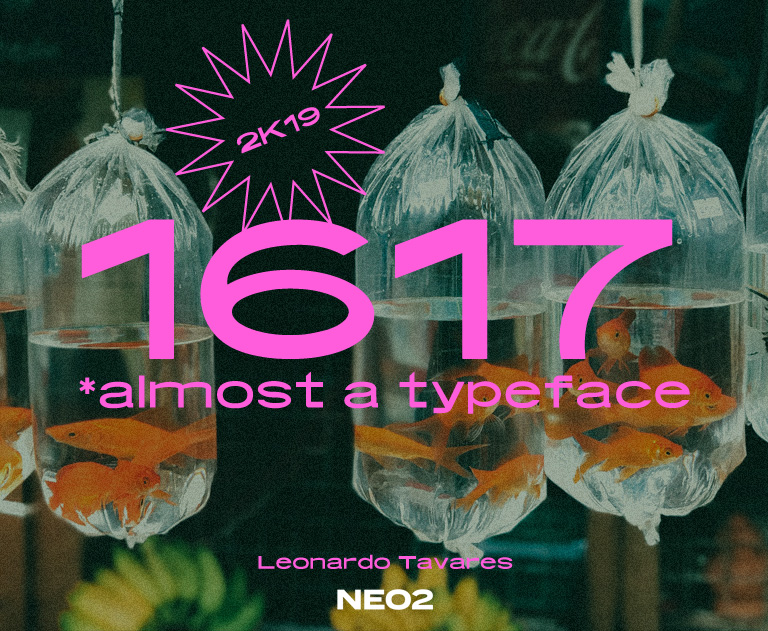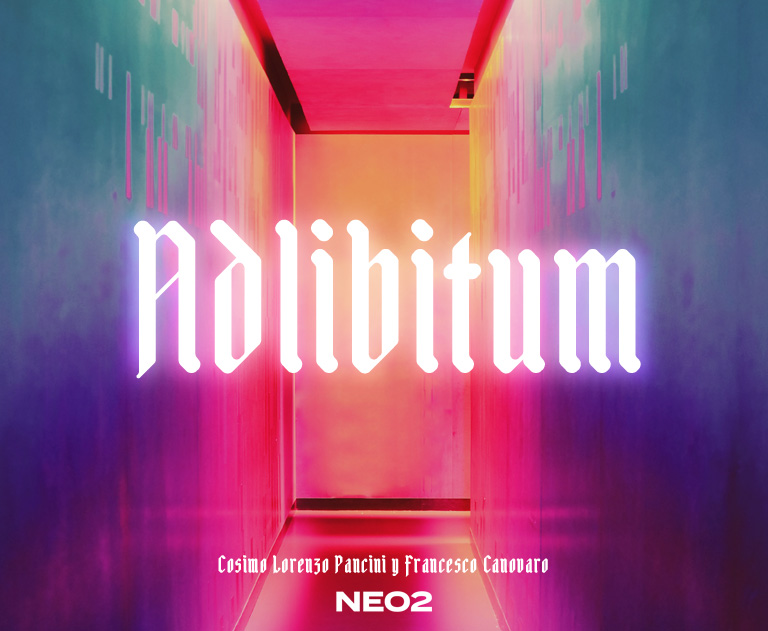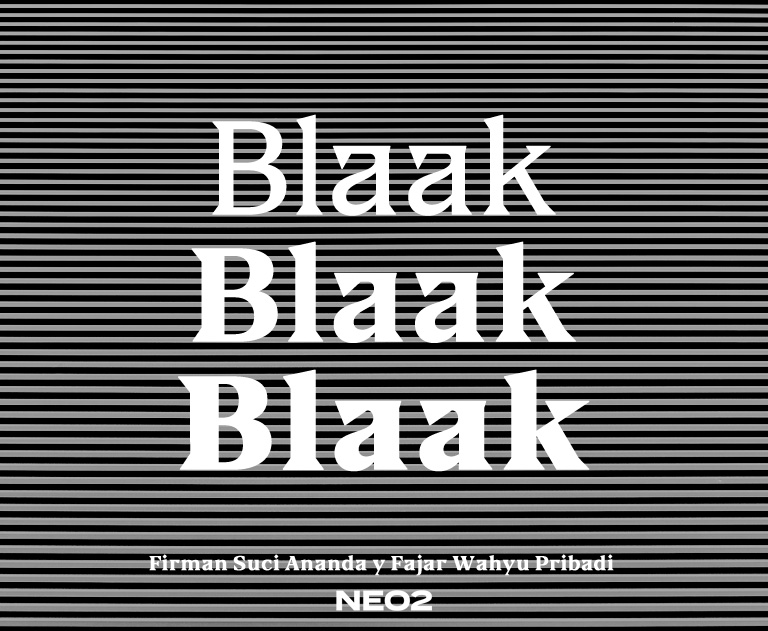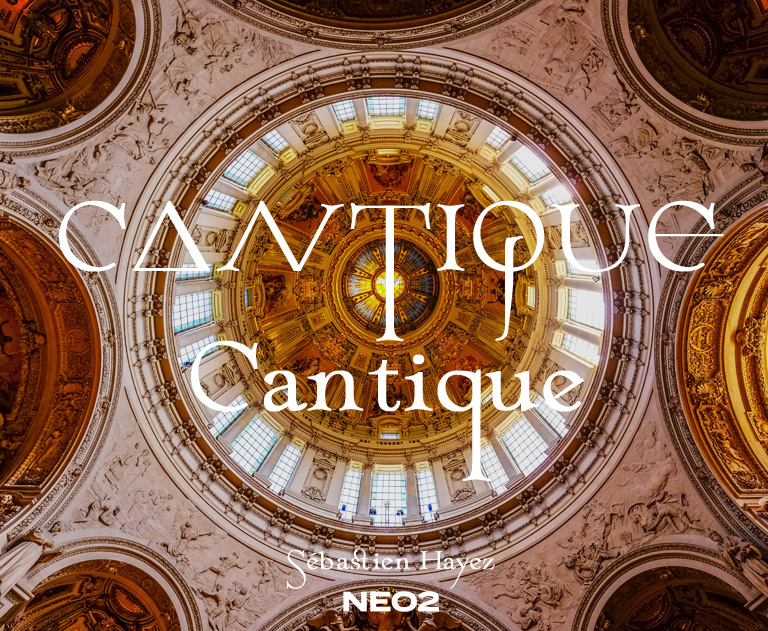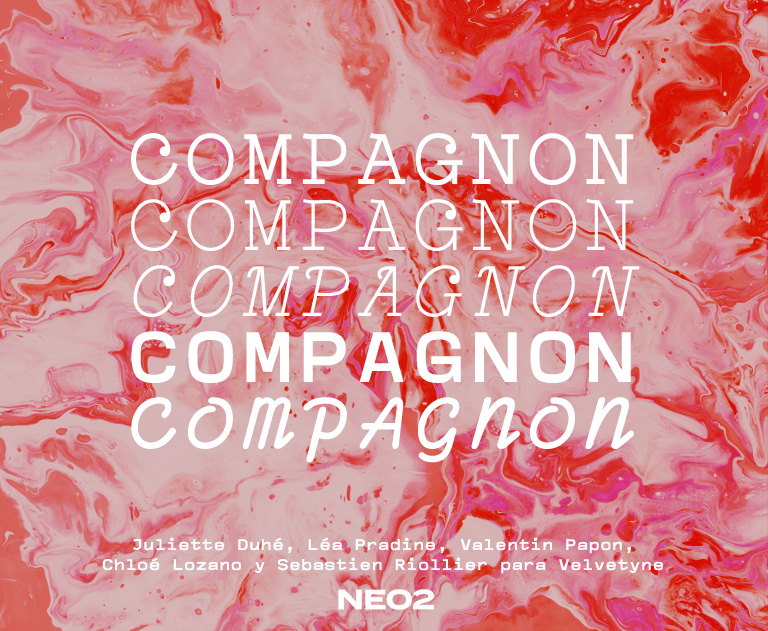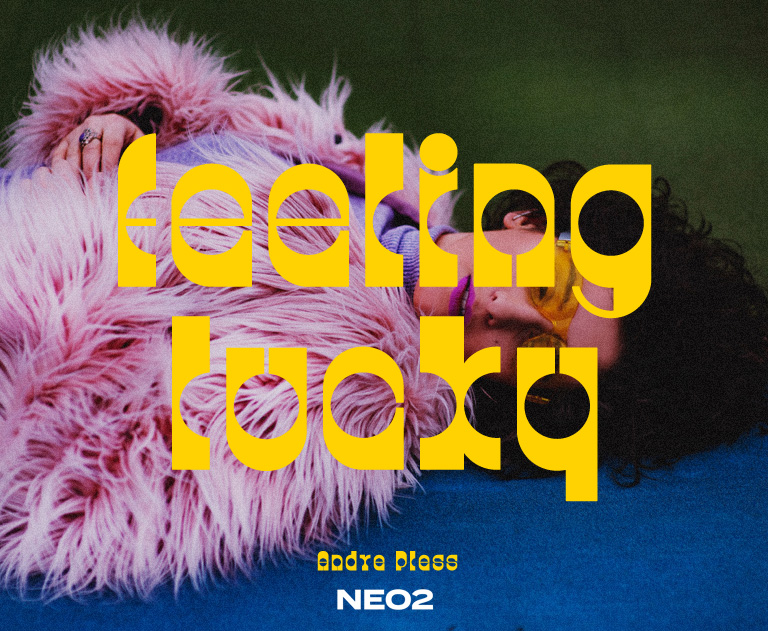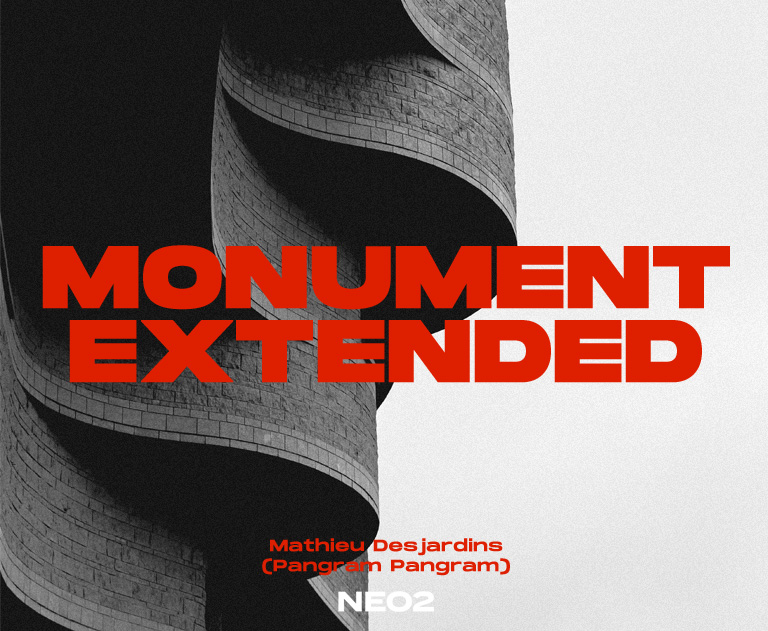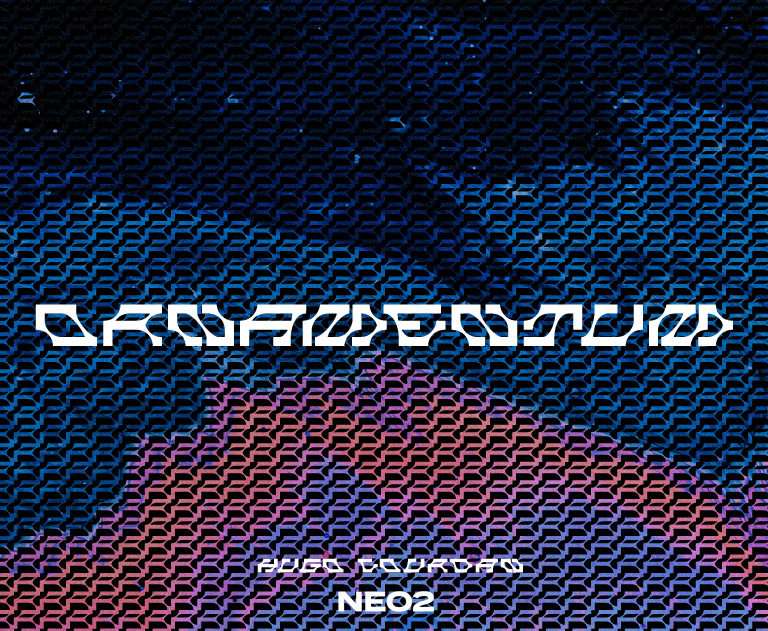
8 tipografías gratuitas que ya deberías tener
Te hacemos una selección de 8 tipografías gratuitas que deberías tener ya en tu ordenador. Las tipografías son una de las herramientas más importantes para los diseñadores, y sabemos que a veces es abrumador la cantidad de ellas que hay.
Pero en Neo2 nos gusta pensar que en la variedad está el gusto. Por eso, hemos creado esta selección de tipografías de distintos estilos que ya deberías tener en tu repertorio.Todas pertenecen a nuestra colección de tipografías gratuitas disponibles para que cualquier fan de Neo2 pueda descargarlas. En esta recopilación hemos escogido algunas de las mejores de los últimos meses. Y nos preguntamos, ¿por qué elegir? Son gratuitas, ¡puedes tenerlas todas!
En esta lista te explicamos qué cualidades hacen a cada tipografía tan especial, y te las mostramos con estos sencillos especímenes que hemos diseñado.
1) Monument Extended, por Mathieu Desjardins (Pangram Pangram)
Esta tipografía gratuita tiene una estética brutalista y muy contemporánea. Se caracteriza por el grosor tan fuerte de sus líneas y por la proporción de sus letras, que son anchas y de baja altura. Estas dos características hacen que sea una tipografía muy densa y, por lo tanto, muy potente. Incluso con esta fuerza, destaca también su simplicidad y minimalismo formal, con formas geométricas, ángulos rectos y curvas agradables que hacen que sea una tipografía muy limpia y útil.
Monument Extended es una tipografía muy completa, con caja alta, caja baja, números, signos de puntuación y símbolos.
El diseñador de esta tipografía gratuita es Mathieu Desjardins, que pertenece a Pangram Pangram, un colectivo de diseño y fundición tipográfica que crea muchas tipografías de estilo contemporáneo gratuitas para uso personal.
2) Adlibitum, por Francesco Canovaro y Cosimo Pancini
Esta tipografía gratuita es de tipo display. Se basa en las tipografías medievales de estilo gótico, modernizando esta estética. Utiliza formas geométricas para crear letras altas y estrechas con ángulos de 45 grados muy característicos. Adlibitum consigue tener una esencia poderosa y altiva que funciona genial en diseños contemporáneos, sobretodo para crear logotipos.
La tipografía tiene tanto caja alta como caja baja, a las que se le añaden números, símbolos y ligaduras. Además tiene tres variaciones que son Light, Regular y Bold.
Adlibitum ha sido diseñada para la revista Neo2 por Cosimo Lorenzo Pancini y Francesco Canovaro, miembros de Zetafonts.
3) 1617, por Leonardo Tavares
Esta tipografía gratuita presenta un estilo muy contemporáneo y futurista. Se basa en letras anchas pero de baja altura, creando un contraste muy interesante entre las dos longitudes. También utiliza desemejanzas arbitrarias en el grosor de sus trazos que le dan una esencia irregular y digital, recordando un poco a la estética glitch.
1617 dispone de caja alta, caja baja, números y una buena cantidad de símbolos y signos de puntuación.
La tipografía gratuita fue diseñada en 2019 por Leonardo Tavares, un joven diseñador y tipógrafo brasileño al que le gusta la experimentación y creación de tipografías distorsionadas e irregulares.
4) Cantique, por Sébastien Hayez
Cantique es un tipografía contemporánea que utiliza elementos de tipografías romanas y griegas para crear letras muy airosas y ligeras. Usa contrastes muy distinguidos en el grosor de las líneas, algunas muy finas, otras más potentes. También alarga las descendentes de algunas letras creando una sensación de elegancia caligráfica.
La tipografía gratuita es muy expresiva y denota un claro estilo sofisticado y a la vez desafiante, y aunque de estética antigua, es muy actual.
Cantique tiene versión en caja alta y en caja baja, cada una con sus interesantes detalles. También tiene símbolos y números.
Esta tipografía gratuita ha sido diseñada específicamente para Neo2 por el diseñador francés Sébastien Hayez, que destaca en muchos ámbitos del diseño gráfico y la ilustración.
5) Blaak, por Firman Suci Ananda y Fajar Wahyu Pribadi
La tipografía gratuita Blaak es una reinterpretación de las tipografías clásicas modernas y egipcias. Su principal característica es el grosor de sus líneas, así como el contraste con líneas más finas. Sus remates son definidos y gruesos, con ángulos puntiagudos, que se equilibran muy bien con las curvas de las letras. El estilo de la tipografía Blaak es potente y elegante a la vez y puede utilizarse para textos medios o cortos, así como para display. Funciona muy bien en diseños editoriales.
La tipografía tiene caja alta, caja baja, numeración y signos de puntuación. Además, tiene distintos estilos que varían su grosor: Regular, Medium, Semibold, Bold, Extrabold y Black.
Esta tipografía gratuita ha sido diseñada por Firman Suci Ananda y Fajar Wahyu Pribadi.
Puedes descargar esta tipografía gratuita “Blaak” haciendo click aquí.
6) Lucky, por André Pless (Mecanorma)
8 tipografías gratuitas que ya deberías tener
Esta tipografía gratuita de tipo display tiene una extravagancia conquistadora. Utiliza formas redondas muy prominentes en sus contraformas y las letras son alargadas y tienen un grosor muy elevado. La tipografía Lucky juega mucho con los contrastes entre líneas finas y formas corpulentas, y entre ángulos puntiagudos y círculos perfectos. Su esencia es muy retro, recordándonos al mismo tiempo al Oeste americano y al estilo de los años 70. Es perfecta para crear títulos súper expresivos de una determinada estética.
Lucky, creada en 1972, tiene versión en caja alta, en caja baja, con números y algunos símbolos.
La tipografía gratuita Lucky fue diseñada por André Pless (Mecarnorma) en 1972 y digitalizada y cedida a Neo2 por Andrea Bianchini en 2019.
Puedes descargar esta tipografía gratuita “Lucky” haciendo click aquí.
7) Compagnon, por Velvetyne
8 tipografías gratuitas que ya deberías tener
Compagnon es una familia tipográfica compuesta de cinco estilos diferentes que tienen una característica en común, todos ellos están inspirados en las tipografías de las máquinas de escribir del pasado, cada uno haciendo referencia a un estilo y a una época específicos. Dos de las tipografías son cursivas, una más ligera y la otra más potente. Las otras tres varían su peso y su utilización de remates.
En conjunto, los cinco estilos de la tipografía gratuita tienen una estética retro y chic muy expresiva, y son perfectos para dar personalidad a tus proyectos. Además, las variaciones de cada versión dan mucha flexibilidad.
Todos los estilos de la tipografía Compagnon tienen caja alta, caja baja, números y símbolos.
La tipografía gratuita ha sido diseñada por Juliette Duhé, Léa Pradine, Valentin Papon, Chloé Lozano y Sebastian Riollier, para la fundición francesa Velvetyne.
Puedes descargar esta tipografía gratuita “Compagnon” haciendo click aquí.
8) Ornamentum, por Hugo Jourdan
8 tipografías gratuitas que ya deberías tener
La tipografía gratuita Ornamentum no es solo de estilo decorativo o display, si no que su función ornamental va un paso más allá. Los glifos de la tipografía están específicamente diseñados para ser utilizados como elementos gráficos con los que generar infinidad de patrones decorativos.
Tiene letras muy experimentales, que están inclinadas y siguen una retícula. Las formas de los glifos de la tipografía tienen mucho contraste entre líneas finas y curvas y cuadrados y rectángulos más gruesos. La variación de estos elementos hace que las letras recuerden a una estructura robótica, esquelética o membranosa.
La tipografía gratuita Ornamentum solo tiene caja alta, ya que las formas de sus letras son muy específicas para crear las líneas o patrones ornamentales.
Esta tipografía gratuita ha sido diseñada por el tipógrafo y diseñador gráfico Hugo Jourdan, basado en París.